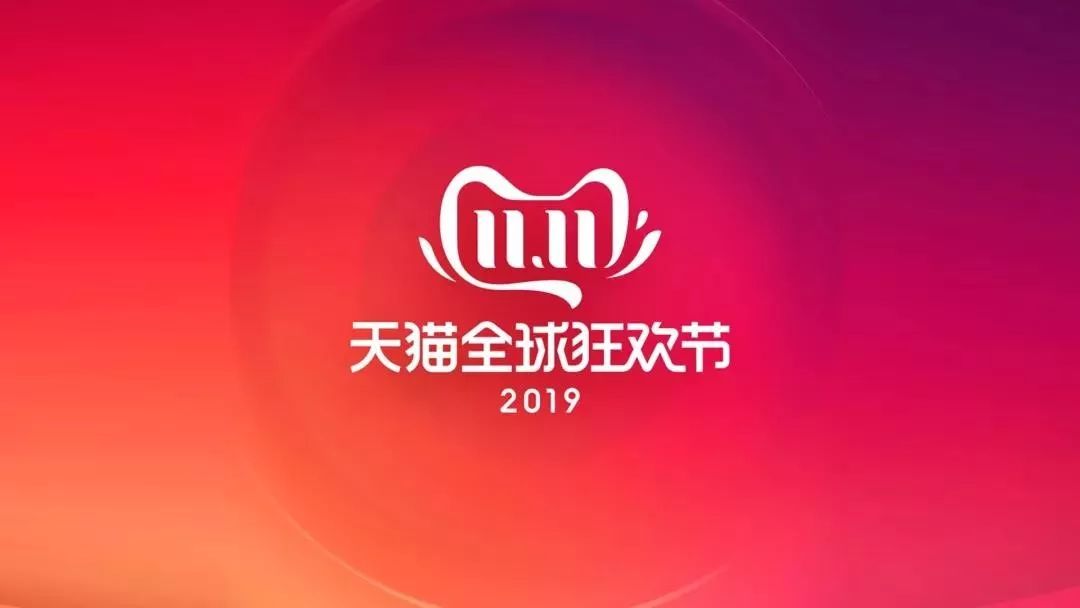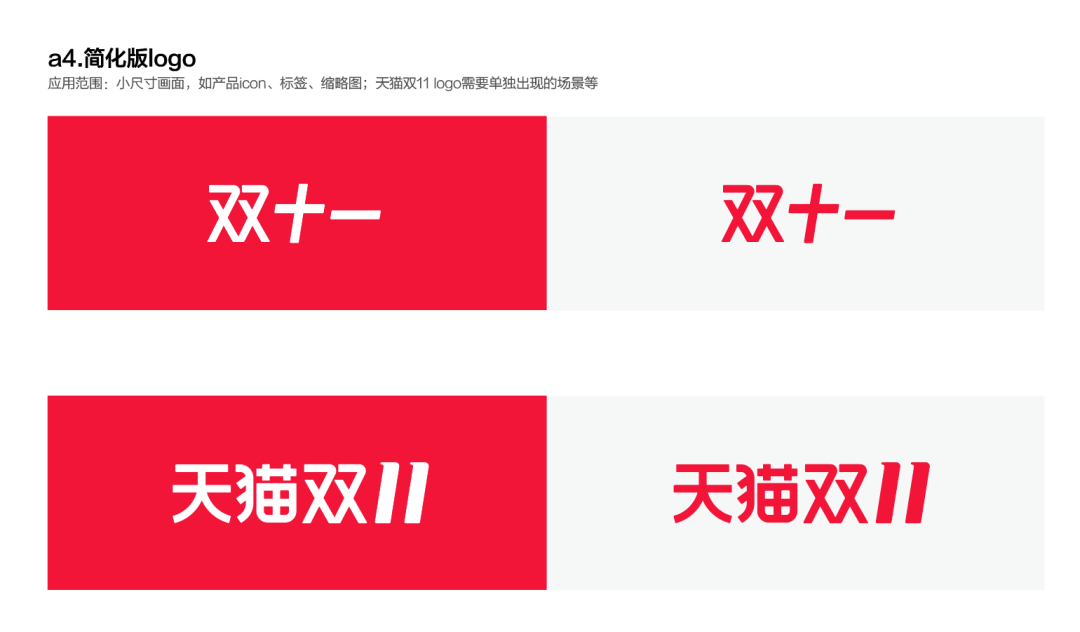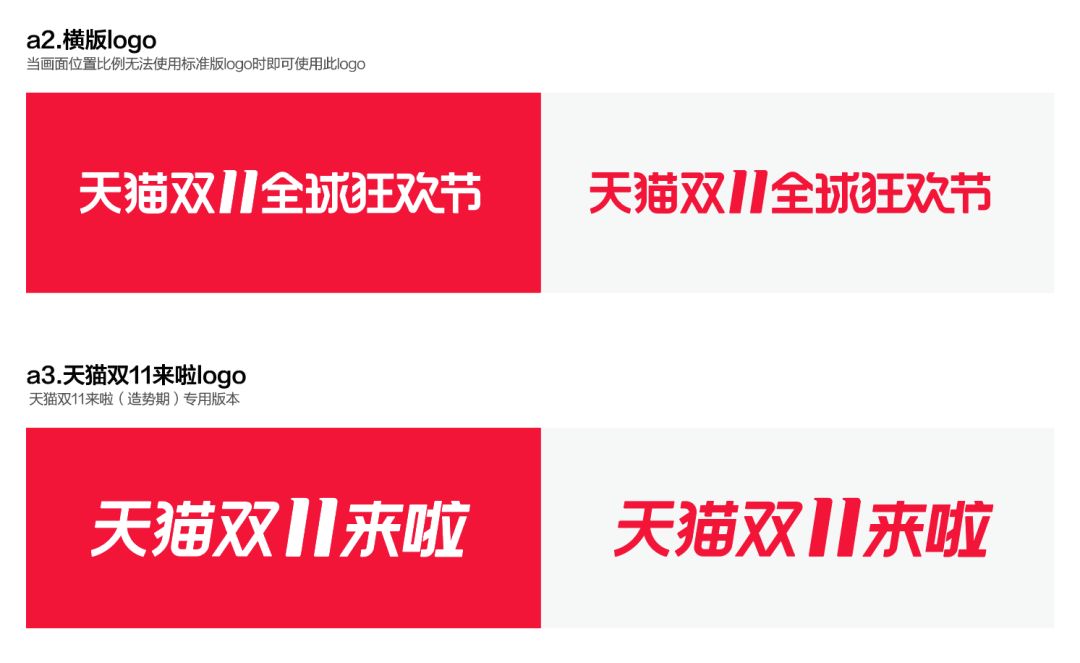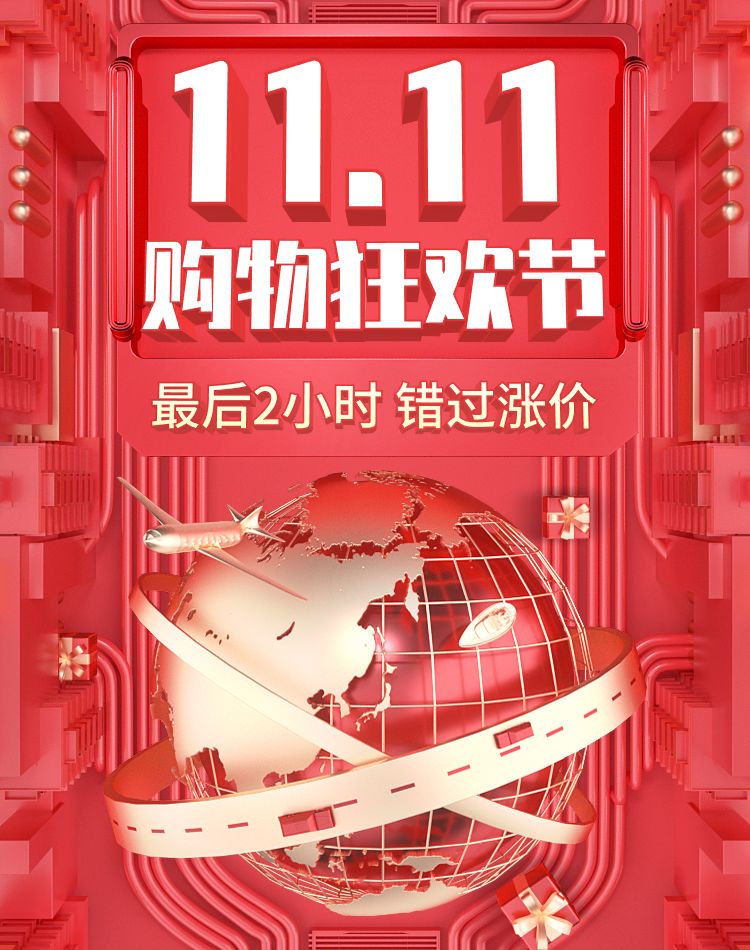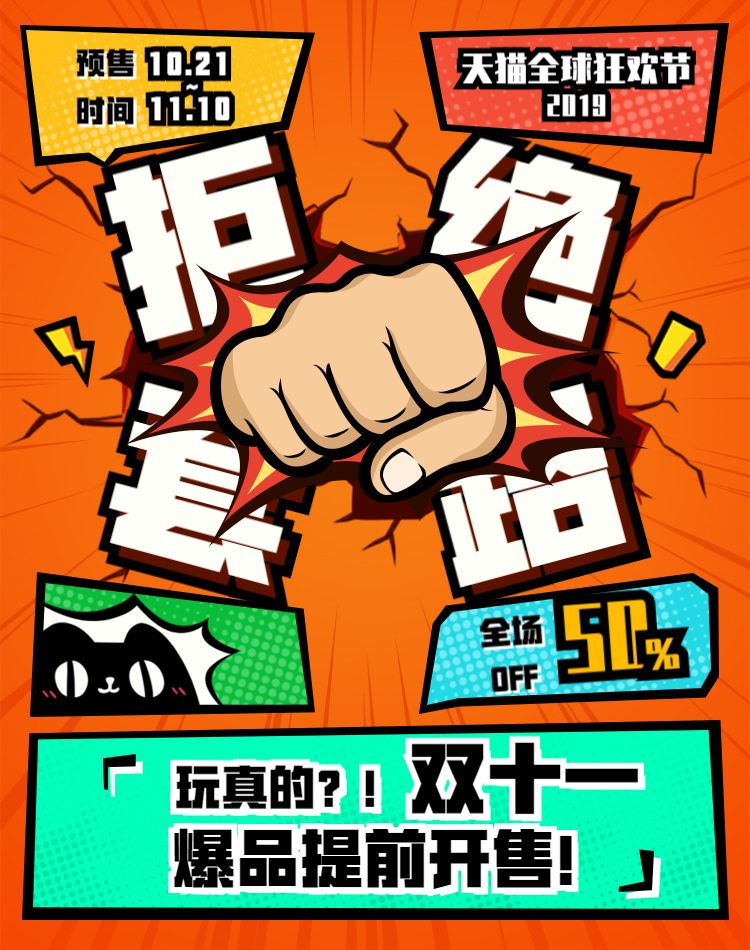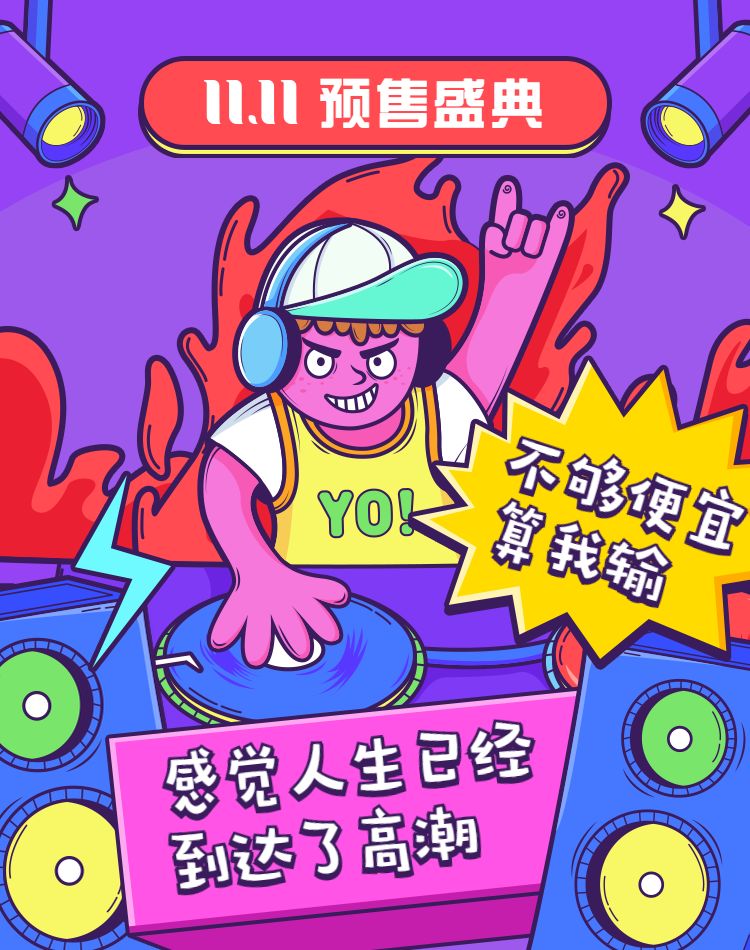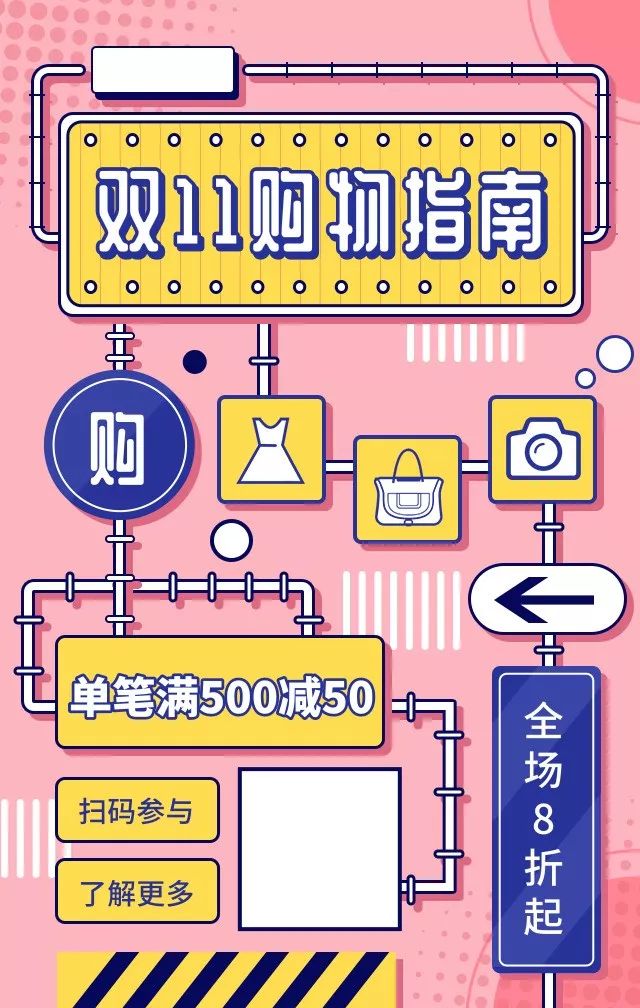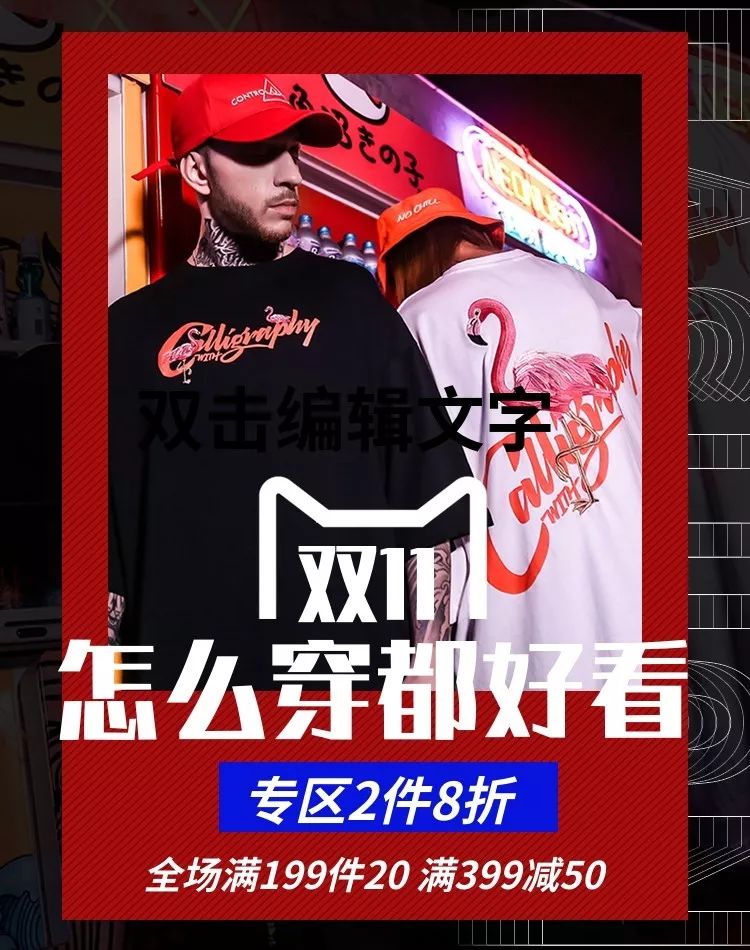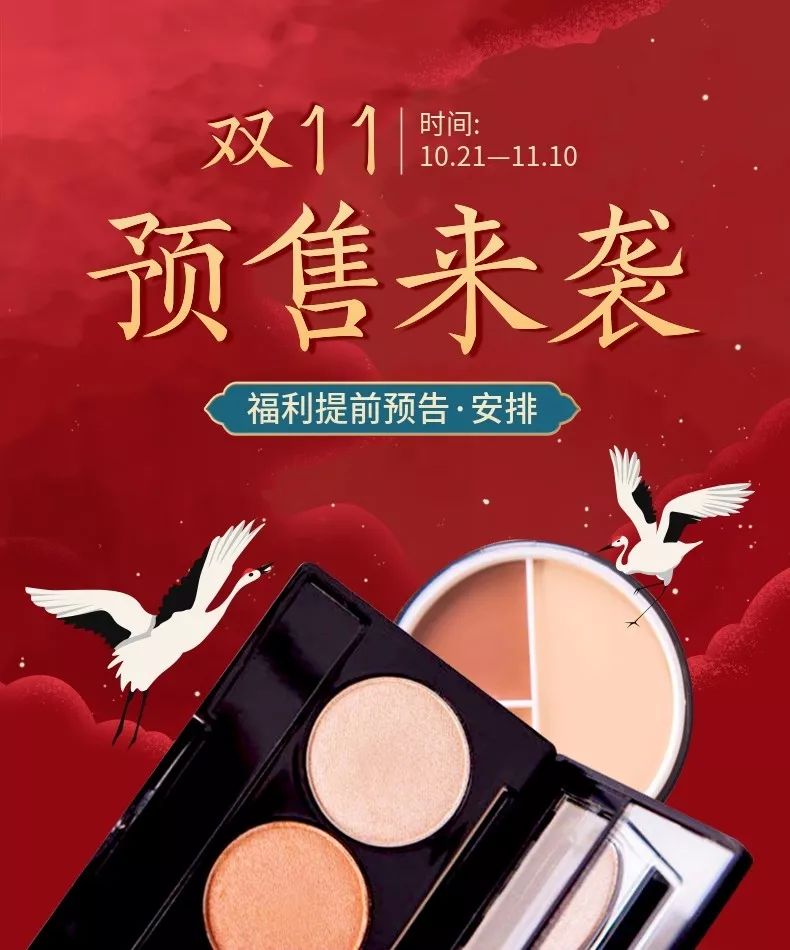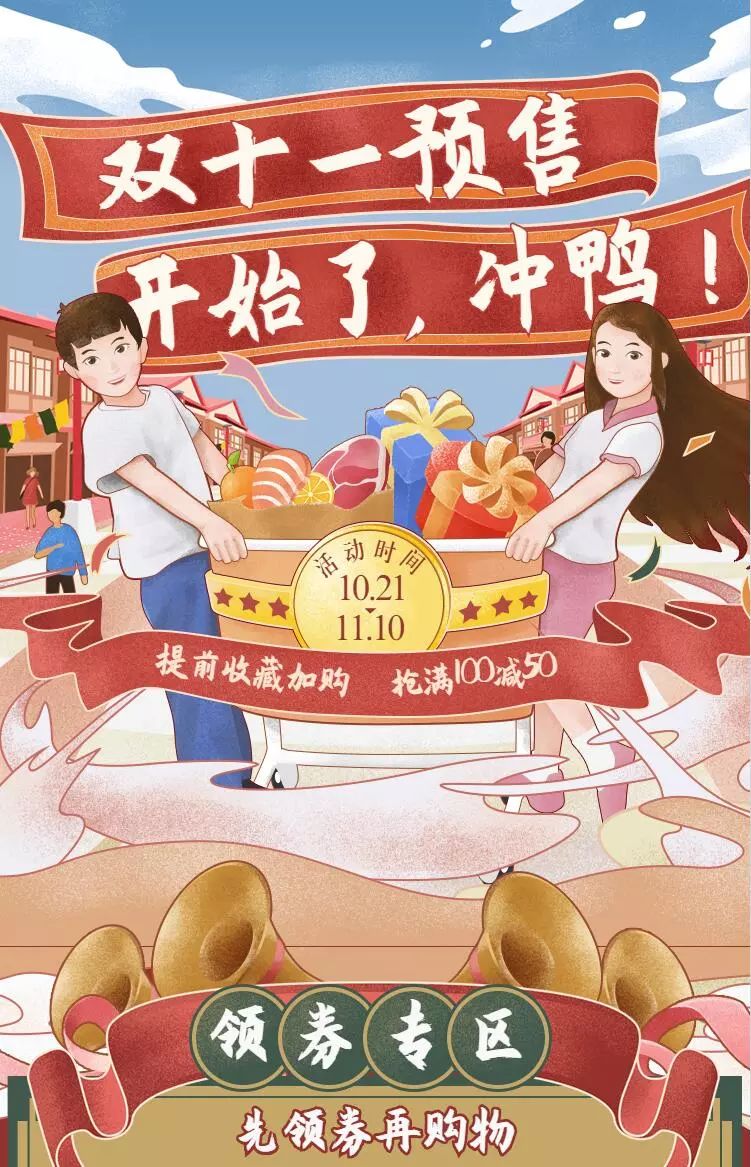
双十一要来啦,什么字体最想让人剁手?
掰掰手指,离双十一(剁手节)没几天了,最忙碌的并不是加购物车的人,而是做页面的设计师,为了让消费者更感性地买买买,他们通常要绞尽脑汁,怎么炫怎么来,先看看官方VI~
像飘带、像浪花,还像机器人,比以往更趋理性,也许是要在5G时代,再创辉煌?
文字logo也比去年简化不少,没有在“11”上做效果变化。
电商海报
▲锐字真言体
▲汉仪力量黑
▲站酷庆科黄油体
▲汉仪跳跳体
▲Aa手写海报
▲庞门正道标题体
店铺首页
▲汉仪字酷堂义山楷
▲庞门正道粗书体
▲阿里汉仪智能黑体
▲锐字真言体
▲汉仪程行
▲汉仪劲楷
轮播banner
▲汉仪黑方
▲庞门正道标题体
▲点字倔强黑
▲点字匹喏曹
▲Aa手写海报
▲逐浪双勾镂线体